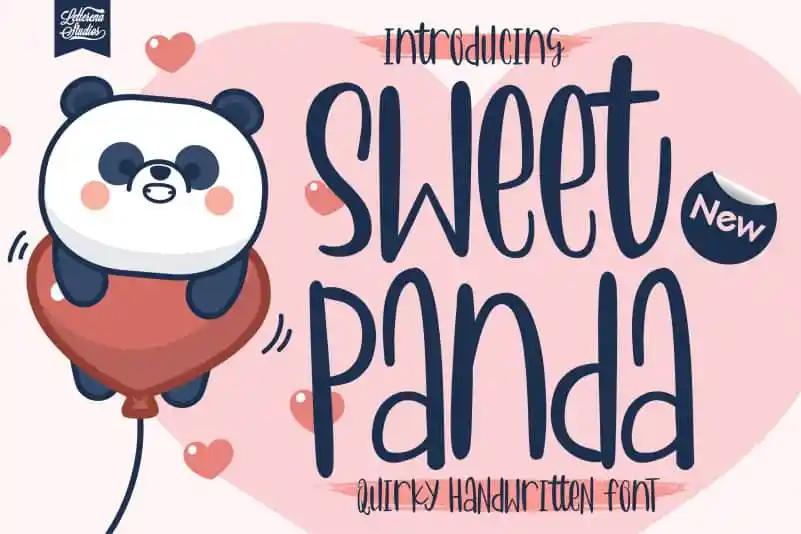
Sweet Panda Display Font – Fonte Grátis
Sweet Panda Display Font
A Sweet Panda Display Font é uma fonte escrita a mão que traz personalidade e um estilo encantador. Seu charme está em sua aparência leve e divertida, perfeita para quem busca algo diferente para seus projetos. Embora não possua características criadas especificamente para essa descrição, ela certamente transmite uma sensação de diversão e alegria que é característica das fontes display. Se você está à procura de algo que seja divertido tanto para olhar quanto para usar em seu projeto visual, esta fonte é uma escolha ideal, especialmente se você valoriza elementos diferentes e únicos. Ela fará sua marca ainda mais peculiar, tornando-a atraente e memorável.